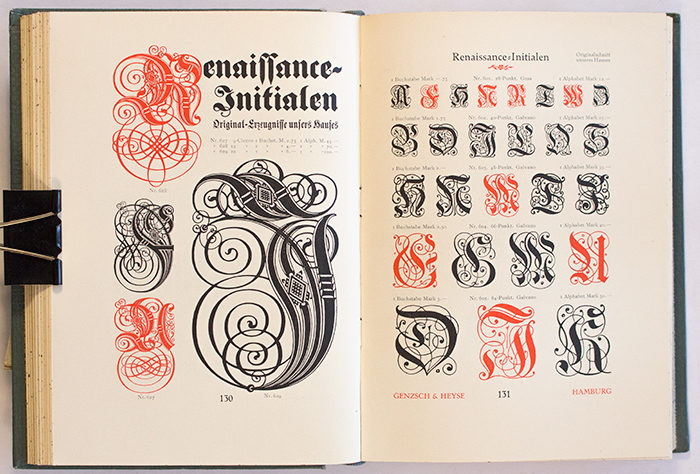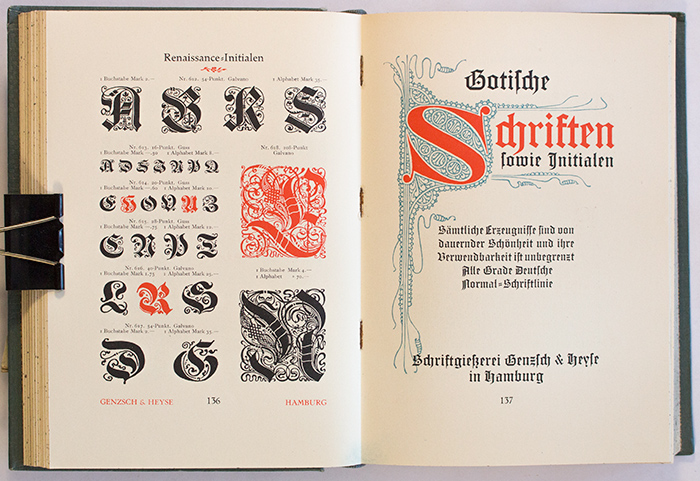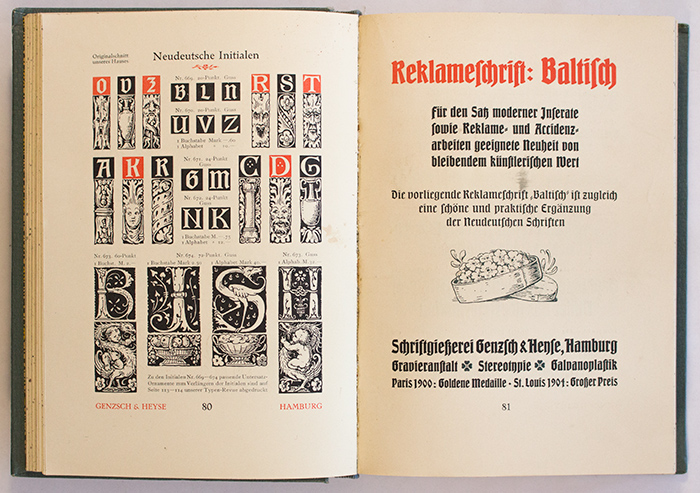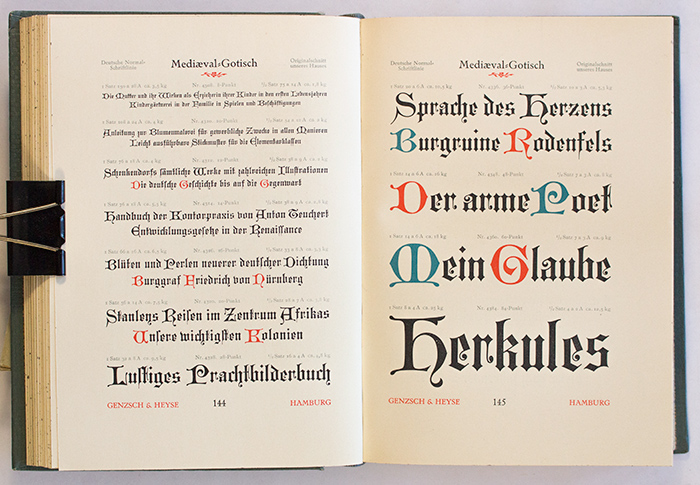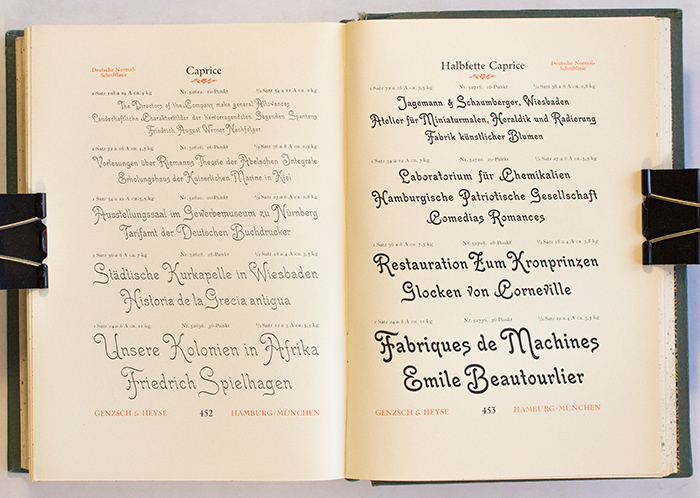
Genzsch & Heyse geht auf ein bereits 1833 durch Johann August Genzsch gegründetes Unternehmen zurück, in das Johann Georg Heyse später als Teilhaber einsteigt. Mit der Übernahme der Lampe’schen Gießerei gelangen viele Schriften des 16. bis 18. Jahrhunderts in die Schriftbibliothek.
Die Umwandlung in eine Aktiengesellschaft erfolgt 1913. Im Jahre 1930 wird die Mehrheit der Aktien durch die Bauersche Gießerei, die H. Berthold AG und D. Stempel AG erworben.
1963 wird die Firma liquidiert und nur die Schilderfabrik bleibt unter altem Namen bestehen.
Die hier gezeigte Handprobe mit 508 Seiten stellt die wichtigsten Schriften der Gießerei Anfang der 1910er Jahre vor.